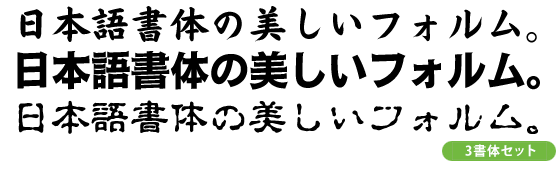
「伝わる和テイストの書体」タイトル・装飾向け3書体パック
MotoyaTohitsuLiteN-W6,SMotoyaOkaiLiteN-W5,MotoyaKoinLiteN-W5
「落ち着いた雰囲気にしたい」「和の空気感を出したい」――そんな時にぴったりの3書体をセットにしました。
Sモトヤ大楷、モトヤ刀筆、モトヤ古印体は、それぞれ異なる個性を持ちながらも、共通して“日本らしい情緒”や“あたたかみ”を感じさせる書体です。
和食店や旅館、観光イベントのチラシ、商品パッケージ、年賀状、同人誌のタイトルなど、和テイストを必要とするあらゆる場面に自然に馴染み、雰囲気づくりをサポートします。どれも太めで視認性が高く、印象づけたいタイトルや見出しに最適。派手すぎず、品よく“伝わる”和の表現が可能です。